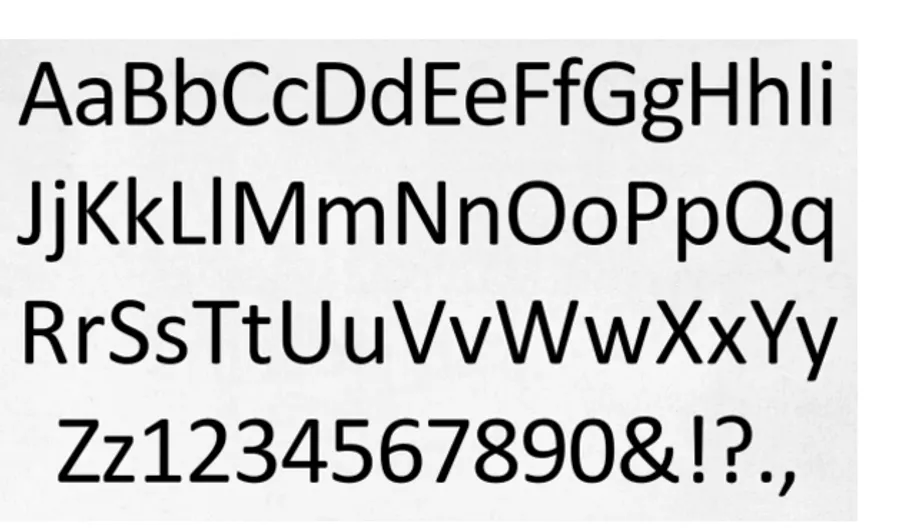
史上最致命字型!微軟 Calibri 字型涉入巴基斯坦政治醜聞案,甚至可能將導致巴基斯坦總理下台
我們每天打開電腦,一開始編寫文件,離不開就是要使用字型。微軟正黑體、細明體、華康少女體⋯⋯諸如此類的,大家每天都在用,卻不怎麼在意自己用了什麼字型。不過,微軟有個Microsoft’s Calibri font 字型,現在可能為字型家族光宗耀祖了。這個字型現在成為巴基斯坦全國人民的焦點,涉入了當地的政治醜聞案,甚至還可能因為它而把總理拉下台。堪稱史上最致命的字型。
聽起來很扯對不對?但這是嚴肅的政治新聞。在今年五月份,巴基斯坦的總理因為之前的巴拿馬文件所爆出的資料,而遭到當地調查單位的調查。而現在調查小組的結果出爐,調查小組認為總理Nawaz Sharif的家人在這次的調查中說謊。
在55頁的調查報告中,調查小組表示巴基斯坦總理的女兒給他們的文件中,這些文件試圖證明他女兒並沒有由這些離岸資產中得利,不過其中一些聲稱是2006年的文件,其中所用的「Calibri」字型,是一直到2007年一月三十一日才由微軟推出的。因此調查小組認為第一家庭在這次調查中提供了偽造的文件、蓄意說謊。
巴拿馬文件中顯示了巴基斯坦的總理三個孩子名下擁有離岸公司以及資產,而這些並沒有被包含在第一家庭的財務報告中。因此調查小組花了兩個月的時間,調查第一家庭的財務狀況。但是現在因為這些被認為是偽造的文書,調查小組判斷第一家庭隱瞞了他們的收入。
這恐怕是有史以來因為一個字型所鬧出過最大的政治新聞了。因為一個微軟的字型,可能會導致一個國家的總理下台。
不過,調查小組之所以判定微軟的Calibri字型在2007年才出現,原因是在於Calibri是在2007年推出的Microsoft PowerPoint, Excel, Outlook, and WordPad 中被用成預設字型首次公開。但是,那不代表在那之前Calibri就不存在。
根據Gizmodo網站詢問微軟,微軟表示公司的內部系統顯示,這個字型在2004年的pre-release版本就已經出現。而根據字型專家Thomas Phinney之前在撰寫字型歷史的時候曾經寫過,「Calibri字型在微軟「外部」首次出現是在2004年8月9日釋出的Windows Beta版。」而在關於這次的巴基斯坦調查案中,也有網友引用了他的這項文件來抨擊調查單位的武斷。
原作者Thomas Phinney也發現了網友的質疑,因此他提供了新的資訊 「請考慮到pre-release版本的Windows一般來說,不會用來成為一般人文書處理的主力。因此,即使在物理上面的確有可能造成2006年所產生的文件,有些文件中的確會有Calibri字型,但那也不可能會讓所有的文件都使用Calibri字型這件事情合理化。」
畢竟Beta版的Windows一般來說,是提供給工程師以及科技極客用來進行測試之用,也很難想像一個政治家的女兒,會使用Beta版的Windows,還用這個系統來輸出這些重要文件。
而Calibri字型的設計師為荷蘭籍的設計師 Lucas de Groot,他在2002年開始設計Calibri,他自己也就這件事情進行了評論:「為什麼有人會在2006年這一年,選擇了一個當時根本沒有任何人知道的字型,用在他們的文件上?」
經過這個事件,Calibri字型從這兩天開始已經成為全球最知名的字型,甚至他的維基頁面在這幾天也因為被瘋狂修改而暫時關閉修訂功能。不過,其實檢視整份調查報告,或許Calibri字型歷史的發佈日期並非那麼重要,因為調查小組還表示在巴基斯坦第一家庭的調查中發現了大量的異常記錄。